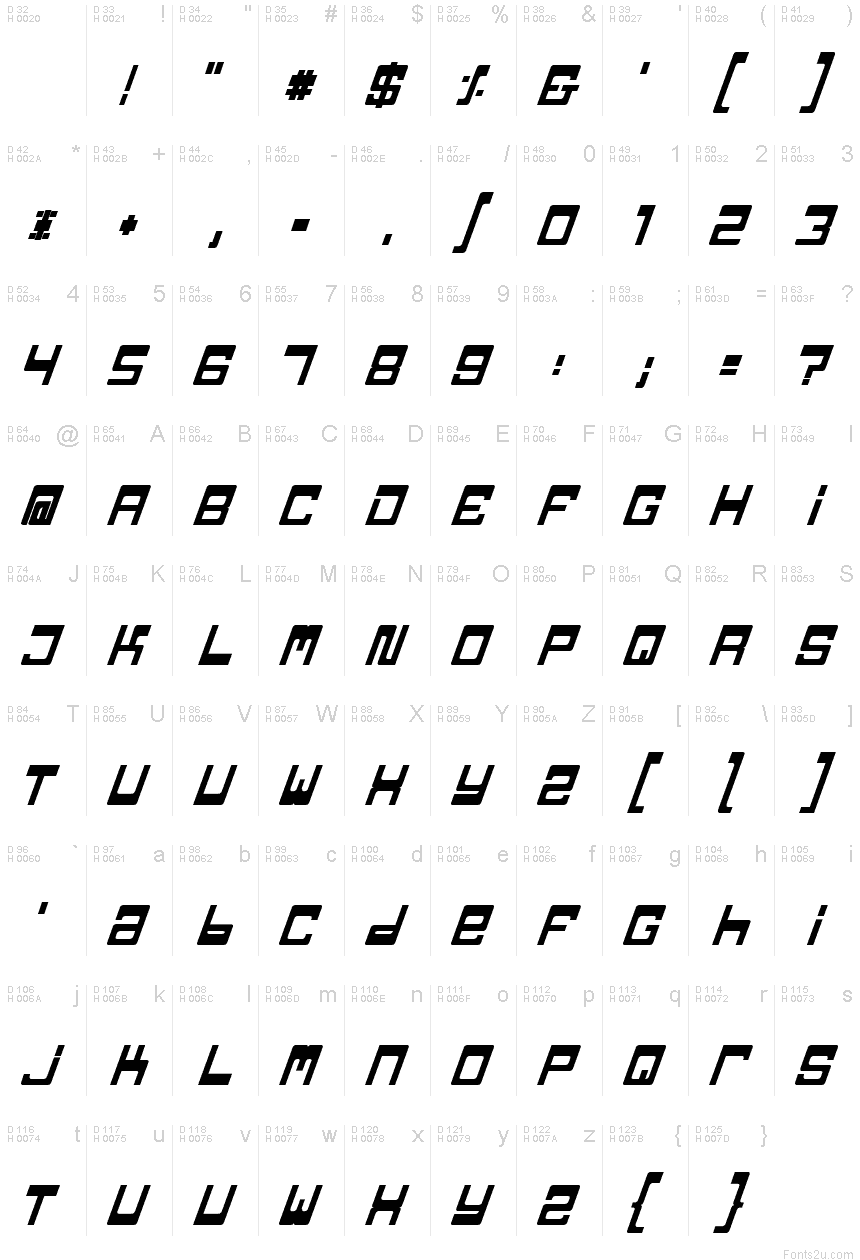
TPF Jaib BoldItalic autorstwa Christopha Scheiblhofera to darmowy, futurystyczny krój typu display, zbudowany z szerokich, pochylonych pociągnięć i precyzyjnie zaprojektowanych wycięć, które sprawiają, że litery przypominają niestandardowe panele maszyn. Pochylenie do przodu jest niezaprzeczalne.
Jego styl science-fiction pasuje do interfejsów gier i wizerunku e-sportowego, gdzie przycięte łączenia i segmentowane kształty wewnętrzne mogą nawiązywać do pancerzy, obwodów lub grafiki pojazdów, a także nadaje plakatom wydarzeń i opakowaniom technologiczno-przemysłowym szybki, surowy charakter. Głównym odbiorcą są projektanci zajmujący się grami, muzyką elektroniczną, sportami motorowymi lub rozrywką spekulatywną, zwłaszcza gdy napisy mają stanowić część szerszego motywu mechanicznego, a nie zwykły, neutralny tekst.
TPF Jaib